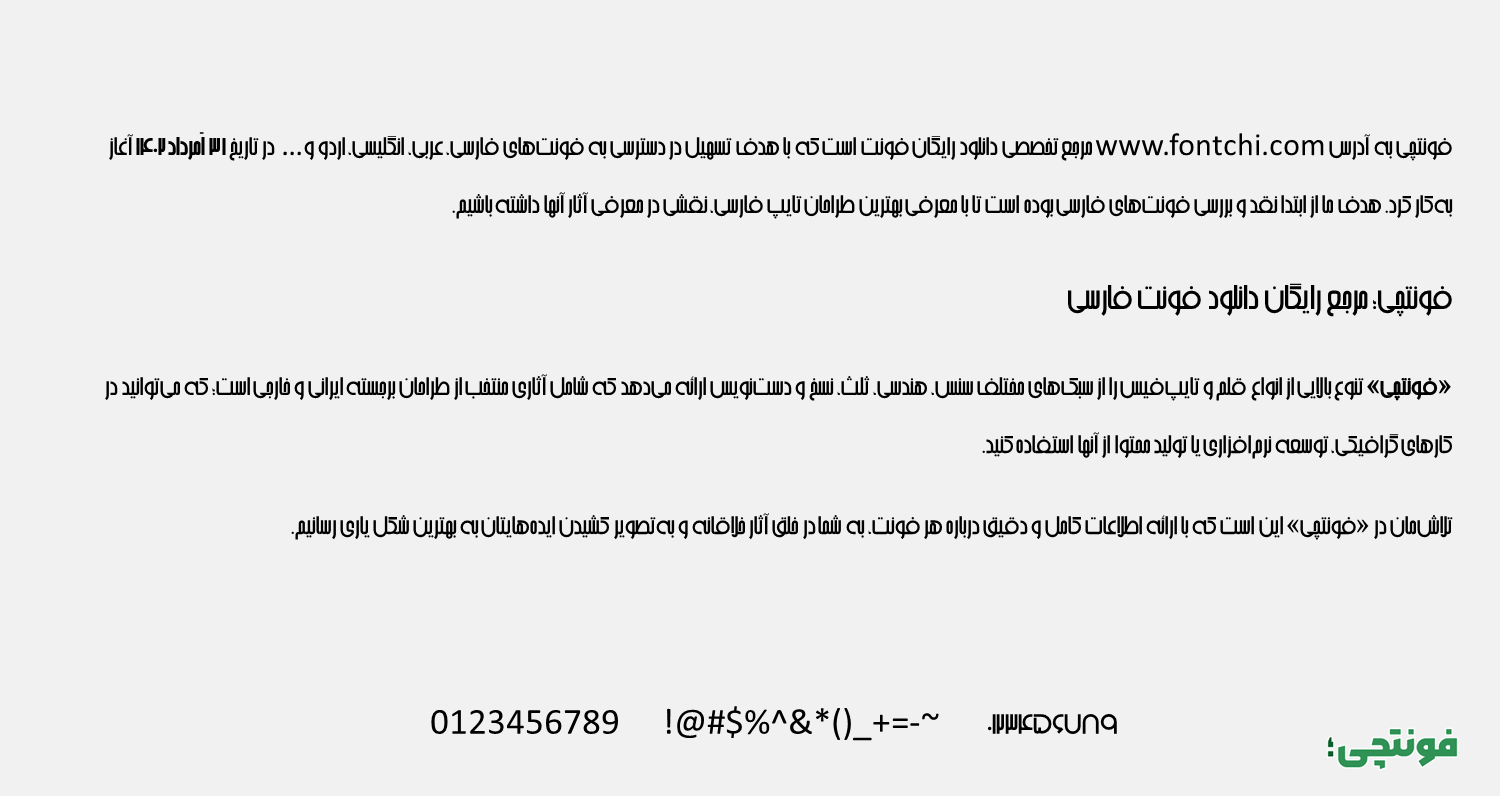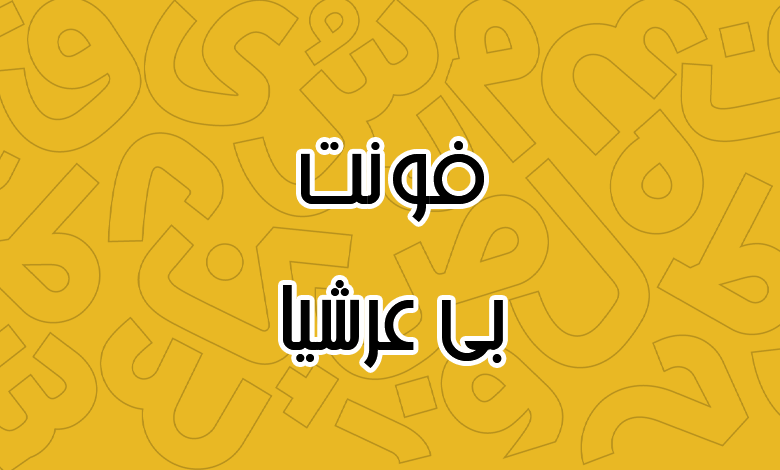
فونت بی عرشیا (B Arshia)
فونت بی عرشیا (به انگلیسی: B Arshia) یک فونت فارسی فانتزی است که در دهه هفتاد توسط برنا رایانه طراحی و تولید شده است. این فونت فارسی با ظاهر خاصی که دارد میتواند در عناوین، خصوصا در زمینه تبلیغات یا کارهای گرافیکی مورد استفاده قرار گیرد که در ادامه به لینک دانلود فونت بی عرشیا دسترسی خواهید داشت.
فونت b arshia با فرمت ttf توسط سازنده ارائه شده است که از زبان فارسی که شامل گلیفهای حروف فارسی، برخی حروف عربی و اعداد است پشتیبانی کاملی دارد. این قلم دارای نسخه Regular معمولی بوده و از سبک Outline نیز پشتیبانی میکند.
در ادامه این نوشته از سایت فونتچی به نقد و بررسی این فونت فارسی جذاب میپردازیم که میتوانید از آن برای زیبا سازی متون استفاده کنید. اگ بهدنبال فونتی مناسب برای متنهای تبلیغاتی هستید که توجه کاربران را جلب کند، این فونت را از دست ندهید.
پیش نمایش و امکانات فونت بی عرشیا (B Arshia)
قبل از هر چیز باید به سبک طراحی حروف در این فونت دقت کنید که متشکل از ساختار نیمدایره برای گردیها و منحنیها بوده و در حروفی که دارای خطوط قائم و دندانهدار هستند نیز ارتفاع بیشتری درنظر گرفته شده تا فونت دارای ظاهری کشیده باشد.
وزن کلی فونت بی عرشیا نسبتا نازک است که به همین دلیل برای استفاده در متنهای بلند با اندازه فونت پایین خوانایی لازم را ندارد. شاید دلیل این کار هم ساخت قلمی بوده که برای استفاده در اندازههای بزرگ مناسب باشد. اما فونت در سایزهای بزرگ بهخوبی خود را نشان میدهد.
از این فونت برای چاپ روی بیلبوردهای تبلیغاتی، بنرها و المانهای محیطی گرفته تا چاپ روی جلد کتاب، مطبوعات و… میتوان استفاده نمود که نیاز به ساختار فونت فانتزی داشته باشید. اما باید توجه کنید که حتما برای متون کوتاه و با اندازههای بزرگ استفاده کنید که فونت خود را بهتر نشان دهد.
فونت بی عرشیا فارسی همانطور که در تصویر بالا هم میبینید از زبان انگلیسی پشتیبانی نمیکند و برای زبانهای لاتین از فونت پیشفرض سیستم برای حروف استفاده خواهد شد. اما باتوجه به رسمخط یکسان با زبان عربی برای این زبان میتواند تا حدودی پاسخگو باشد.
دلیل اینکه میگوییم «تا حدودی»، این است که این فونت گلیفهای زبان عربی را بهطور کامل پشتیبانی نمیکند و صرفا حروفی که در فارسی مورد استفاده قرار میگیرند تعبیه شده است. به عنوان مثال در بخش حروف خبری از گلیفهای «ک، ی، ه، ئ» یا اعداد عربی «۴۵۶» نیست و از اعداد فارسی پشتیبانی میکند.
سبک نقطهگذاری در فونت بی عرشیا نقطهگرد است که فاصلهگذاری استانداردی هم با اعراب دارند. همچنین فونت از سبک بولد پشتیبانی میکند، البته نه به این معنی که نسخه جداگانه با وزن بولد را داشته باشد؛ بلکه میتوانید به کمک ابزار بولد کردن در انواع نرمافزار ساختار حروف را ضخیم کنید.